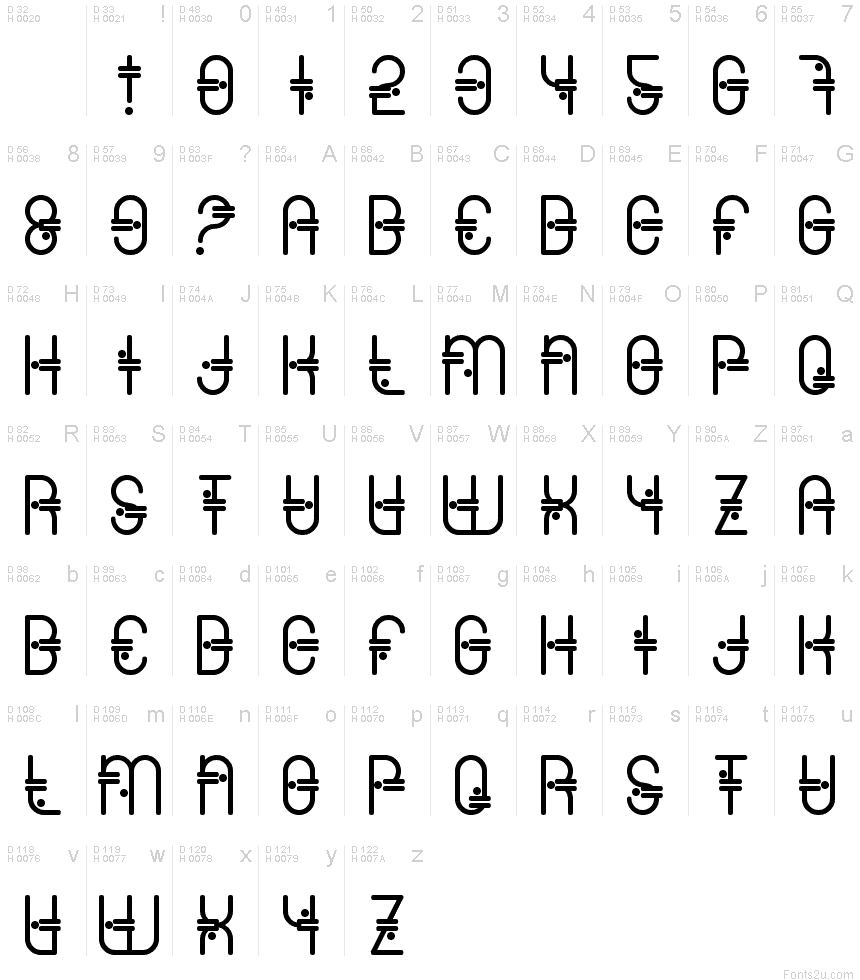
<p>ColonialViper è un font techno gratuito caratterizzato da tratti tubolari e chiusi e da netti tagli orizzontali che bloccano ogni lettera in un ritmo compatto. Gli angoli arrotondati e i punti precisi gli conferiscono un aspetto modulare, quasi simile a un circuito, che risalta istantaneamente su sfondi scuri o vivaci. Abbinalo a un semplice font sans-serif geometrico per i testi più piccoli, così da mantenere leggibili i tuoi layout mentre ColonialViper ruba la scena nei titoli più audaci.</p>
<p>ColonialViper è un font gratuito perfetto per copertine di musica elettronica, poster sci-fi, loghi di videogiochi, branding di eventi tecnologici e grafiche d'impatto per i social media. Lo spessore costante dei tratti e le curve strette creano una texture unificata che risulta allo stesso tempo futuristica e giocosa. Funziona magnificamente anche per adesivi personalizzati, stampe su abbigliamento e titoli di UI sperimentali, dove desideri che la tipografia sembri progettata con cura pur rimanendo accessibile.</p>